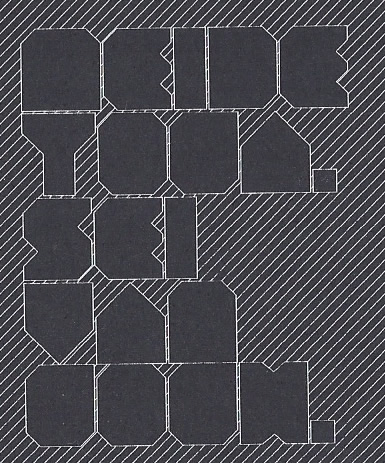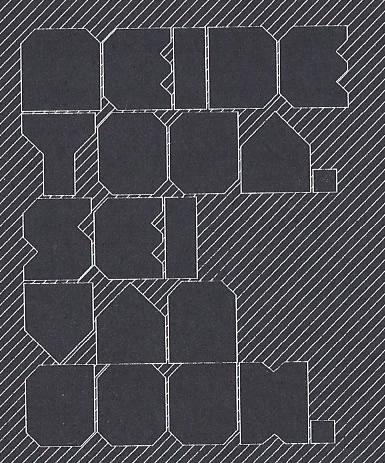
gleich zwei unbekannte schriften
Liebe Typo-Kenner,
darf ich Euch um Hilfe zur Schrifterkennung bitten.
2. ist die DIN Medium, die Oberlängen wurden abgeschnitten.
Zur Schrift unter Punkt 1 habe ich noch ein weiteres Bild einer Schriftart im ähnlichen Stil - vielleicht kennt jemand diese Schrift.
Ich sehe nur eine lesbare Schrift. Was sollen die anderen komischen Zeichen? Kann mir einer mal die Texte mit den obskuren Blöcken in lateinische oder gebrochene Schrift transkribieren? Wer kommt eigentlich auf die Idee eine unlesbare Schrift einzusetzen, gar zu gestalten? *kopfschüttel*
Das ist eben eine Typografik! ;-)
1. strichpunkt;
2. MEIDE YOGA. SEI VAN GOGH.
Danke für die Aufklärung. Wie soll man als normaler Mensch auf so was kommen? Besonders bei Fremdworten und Eigennamen ist Typografik doch fehl am Platz. Das ist ja noch schlimmer als Textura im Versalsatz. *würg* Ich muss jetzt aufhören bevor ...